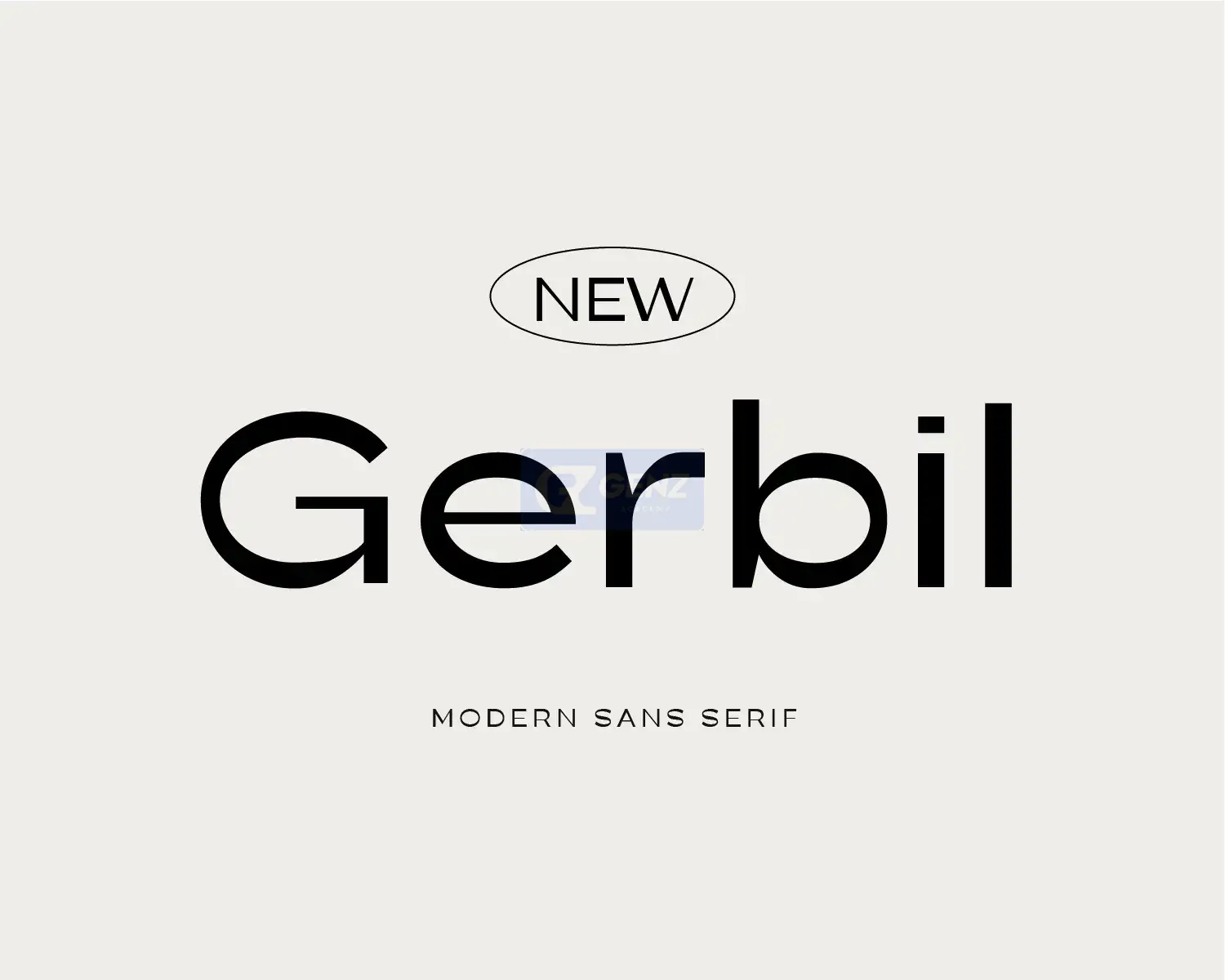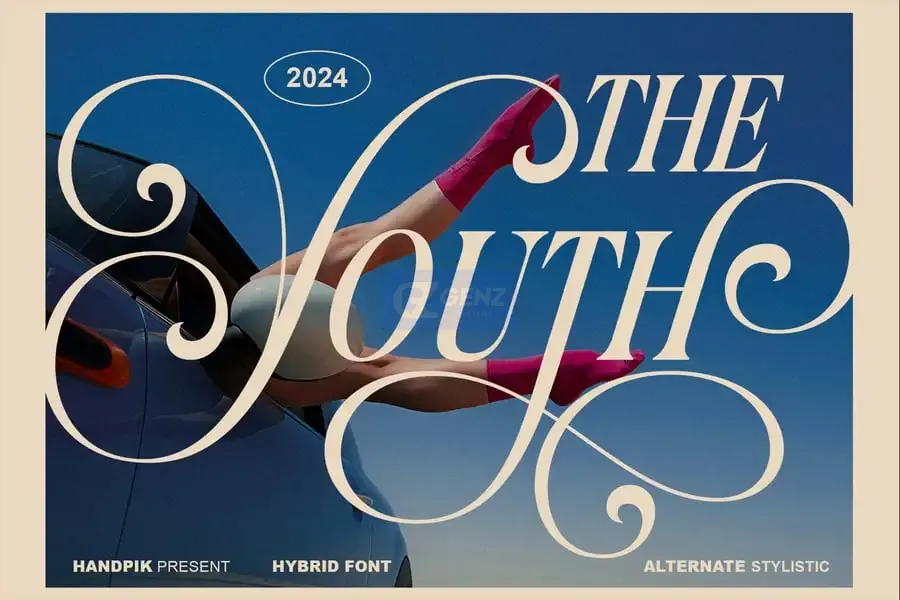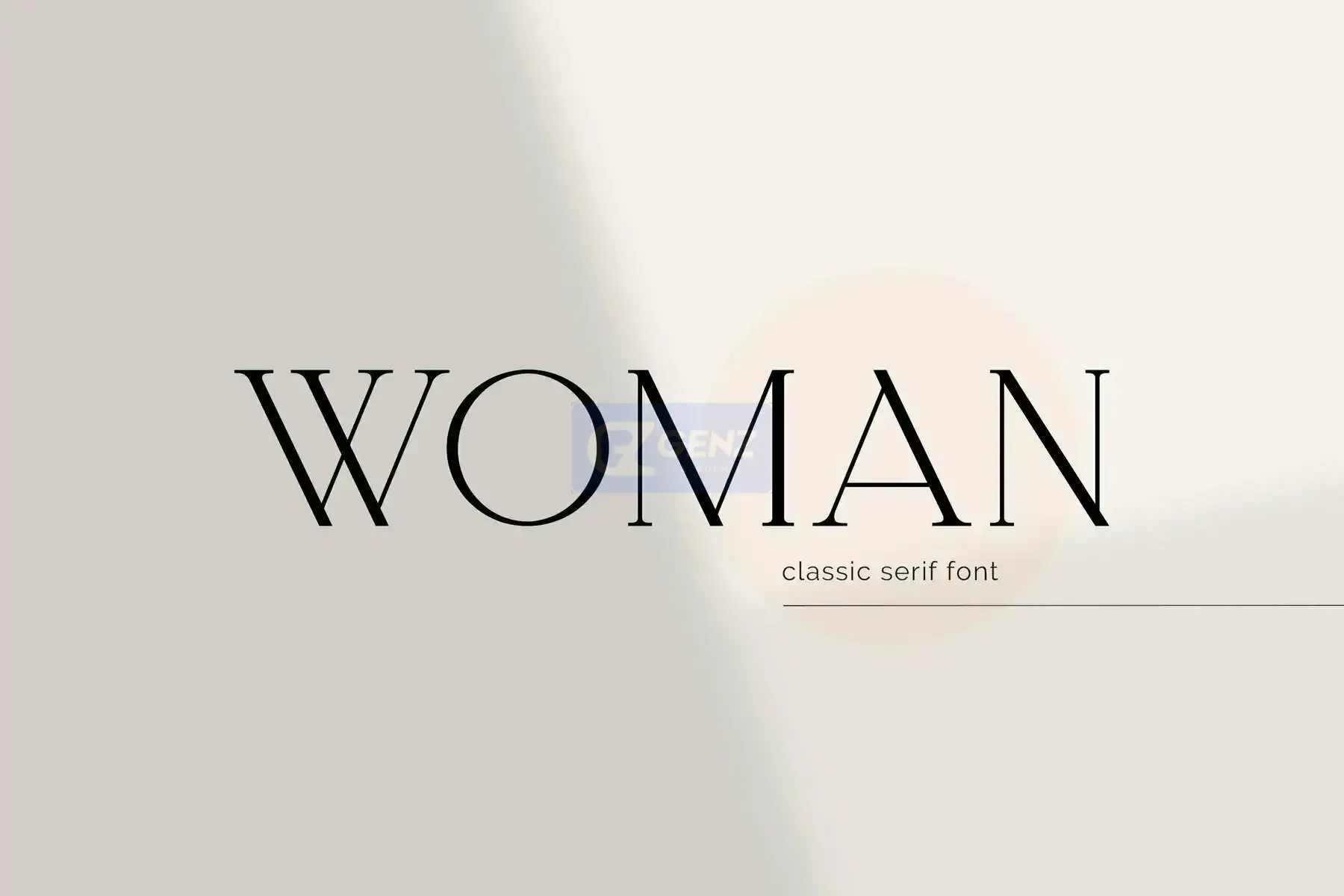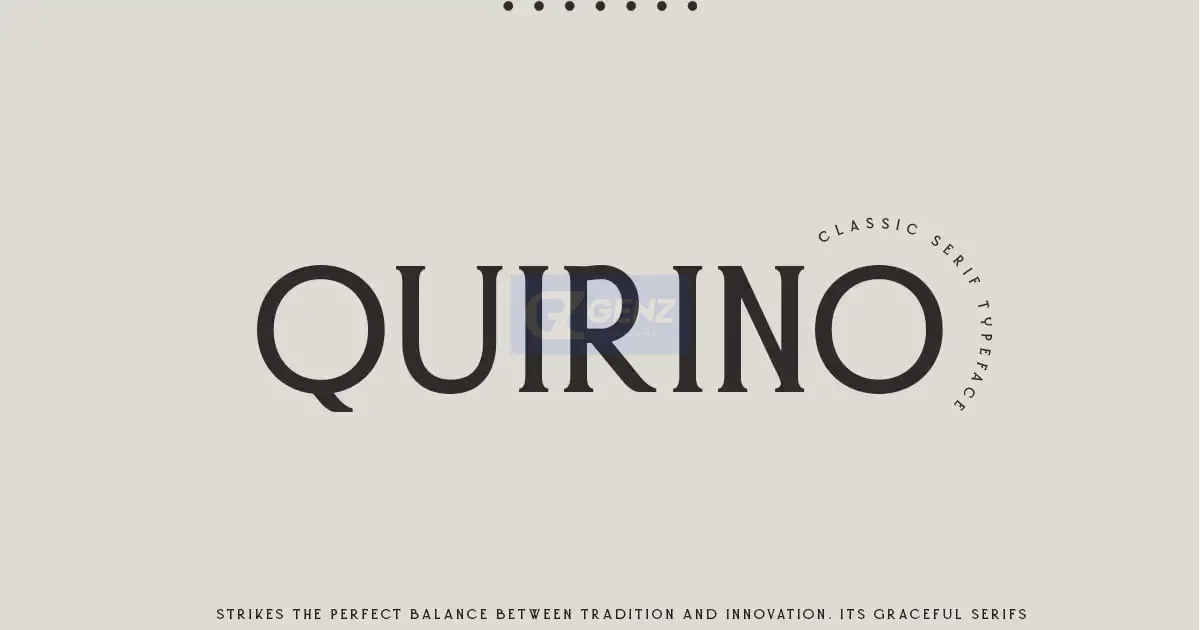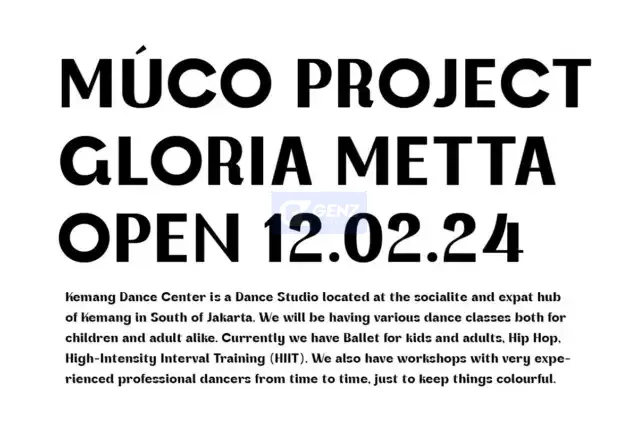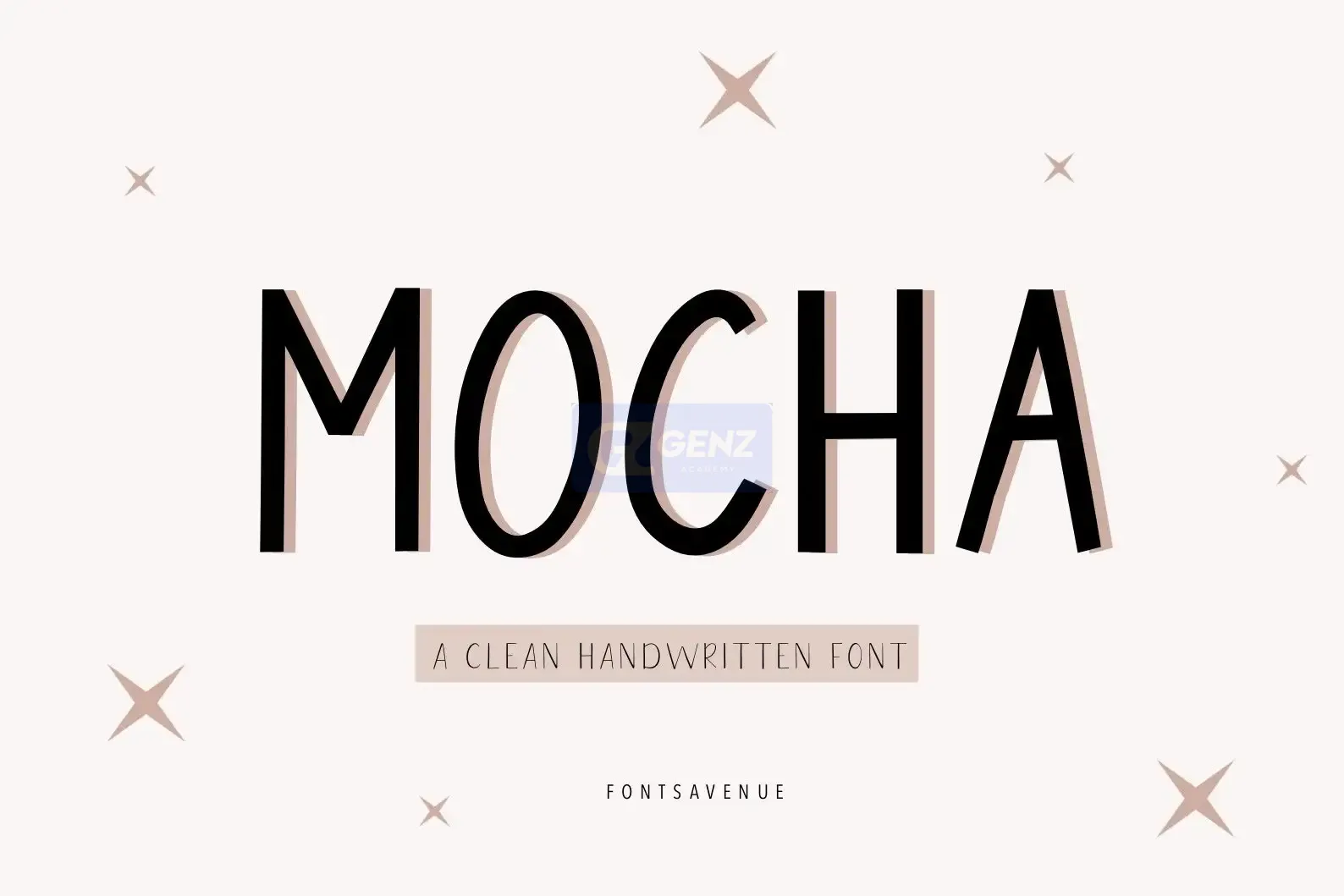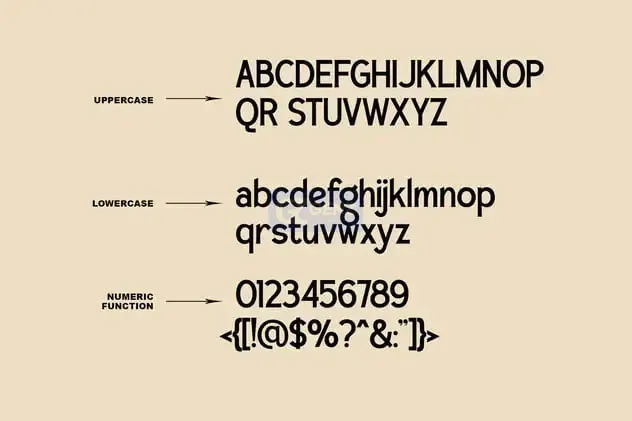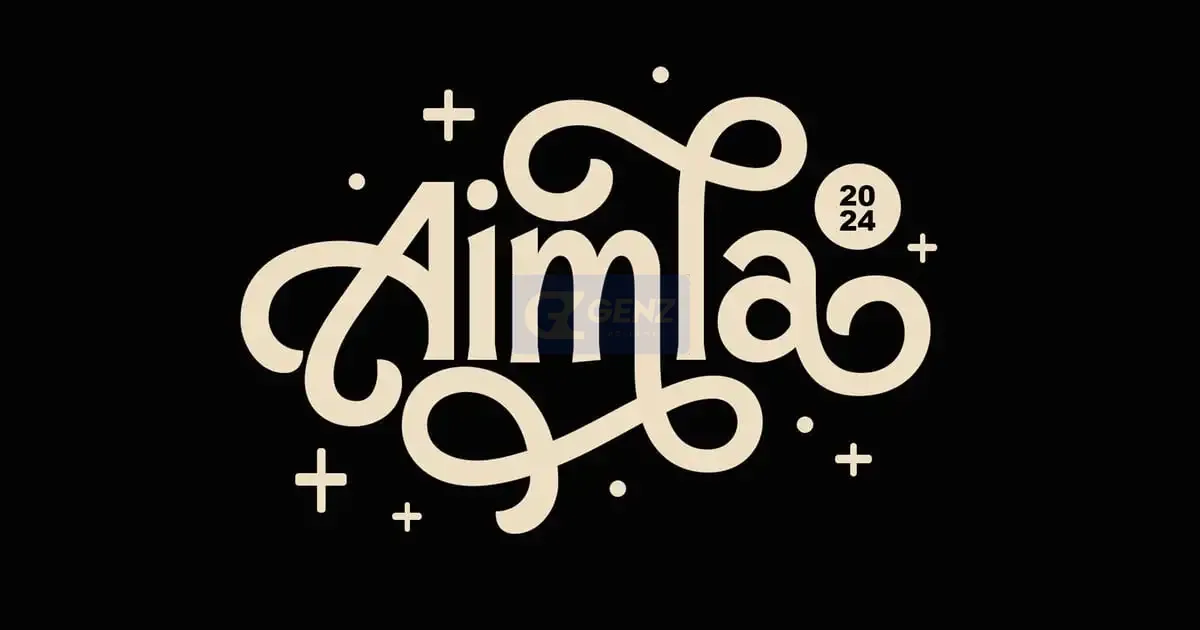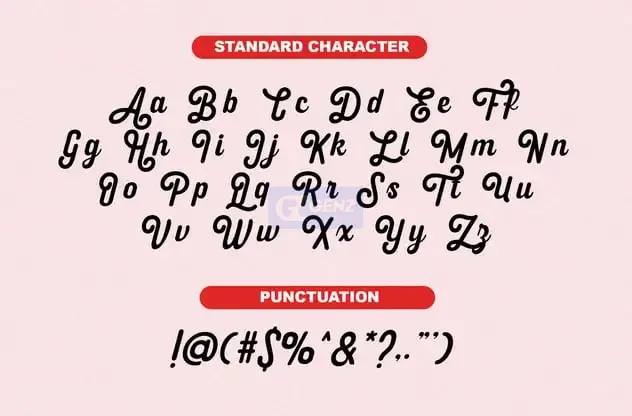
Trong thời đại công nghệ số hiện nay, việc lựa chọn font chữ phù hợp không chỉ tạo nên vẻ đẹp thẩm mỹ cho thiết kế mà còn giúp truyền tải thông điệp một cách mạnh mẽ và ấn tượng hơn. Năm 2025, các nhà thiết kế đồ họa và người dùng cần cập nhật những font chữ mới nhất để đáp ứng nhu cầu sáng tạo. Những font chữ không chỉ đẹp mắt mà còn đa dạng, có thể áp dụng cho nhiều dạng dự án khác nhau từ in ấn đến thiết kế số. Trong bài viết này, chúng ta sẽ cùng khám phá danh sách các font chữ tiếng Anh được yêu thích nhất và những trang web miễn phí để tải chúng về dễ dàng, tạo điều kiện cho bạn nâng cao chất lượng các sản phẩm thiết kế của mình.
Google Fonts: nguồn tài nguyên đáng tin cậy
Nói về Google Fonts, đây được coi là “báu vật” cho các nhà thiết kế không chỉ bởi vì số lượng font phong phú mà còn vì những tiện ích mà nó mang lại. Với hơn 1,800 font chữ mã nguồn mở, Google Fonts là một nơi tuyệt vời cho những ai đang tìm kiếm nguồn tài nguyên miễn phí để làm phong phú cho dự án thiết kế của mình.
Google Fonts không chỉ cung cấp font chữ mà còn hỗ trợ nhiều ngôn ngữ khác nhau, bao gồm cả tiếng Việt. Đây là một điểm cộng lớn, giúp bạn tùy chỉnh thiết kế theo đúng ý muốn mà không gặp phải vấn đề về ngôn ngữ. Ngoài ra, giao diện thân thiện và khả năng tích hợp đơn giản giúp người dùng dễ dàng nhúng các font chữ vào website hoặc dự án của họ.
Một số font chữ nổi bật từ Google Fonts có thể kể đến như:
- Roboto: Font chữ sans-serif hiện đại, dễ đọc, thường được sử dụng cho thiết kế web.
- Lato: Được thiết kế để đem lại sự cân bằng giữa hiện đại và truyền thống.
- Open Sans: Một trong những font phổ biến nhất trên thế giới với độ dễ đọc cao.
Tất cả các font này đều được thiết kế để người dùng có thể tùy chỉnh theo kích thước, màu sắc và độ dày chữ, giúp việc sử dụng trở nên thân thiện và linh hoạt hơn bao giờ hết.
Bảng so sánh một số font chữ nổi bật từ Google Fonts:
| Tên Font | Loại Font | Nơi Sử Dụng |
|---|---|---|
| Roboto | Sans-serif | Thiết kế web, tài liệu |
| Lato | Sans-serif | Website, in ấn |
| Open Sans | Sans-serif | Thông điệp quảng cáo |
Dafont: kho tàng font chữ độc đáo
Khi nói đến việc tìm kiếm các font chữ độc đáo và thú vị, Dafont là cái tên không thể thiếu. Đây là nơi quy tụ của hàng chục ngàn font chữ miễn phí với các chủ đề đa dạng từ cổ điển đến hiện đại, từ dễ thương đến trang nghiêm.
Dafont cho phép người dùng xem trước font trong thời gian thực bằng cách nhập văn bản của riêng mình, giúp xác định font chữ nào phù hợp nhất cho dự án của bạn. Đặc biệt, các font trên này được phân loại thành nhiều nhóm khác nhau giúp bạn dễ dàng tìm kiếm, như script, display, sans-serif, serif, … Đây chính là một ưu điểm vượt trội mà Dafont mang lại, giúp tiết kiệm thời gian cho các nhà thiết kế.
Như một người yêu thích font chữ, bạn sẽ tìm thấy rất nhiều font chữ thú vị tại Dafont. Hãy lưu ý đọc kỹ giấy phép sử dụng để tránh các vấn đề về bản quyền khi ứng dụng chúng trong dự án của mình.
Danh sách một số loại font chữ nổi bật trên Dafont:
- Black Jack: Font chữ viết tay đầy cá tính, thường được dùng cho thiết kế trẻ trung.
- Pacifico: Đem đến hơi thở của tự do và sáng tạo, rất độc đáo và nổi bật.
FontSpace: nền tảng tìm kiếm font chữ hữu ích
Nếu bạn đang tìm kiếm một nền tảng thân thiện và dễ sử dụng để khám phá các font chữ, FontSpace là nơi lý tưởng cho bạn. Với kho tàng hơn 120,000 font, đây là nơi tập trung của nhiều nhà thiết kế nổi tiếng trên thế giới. Giao diện trực quan và dễ điều hướng giúp người dùng tìm kiếm font một cách nhanh chóng và dễ dàng.
Tại FontSpace, người dùng có thể lọc font theo nhiều điều kiện khác nhau như phong cách, nhà thiết kế hay độ phổ biến, từ đó tạo ra bộ sưu tập font chữ yêu thích. Mỗi font chữ đều đi kèm với thông tin rõ ràng về giấy phép sử dụng, đảm bảo cho bạn rằng không gặp rắc rối về pháp lý sau này.
Bên cạnh đó, FontSpace cũng khuyến khích người dùng chia sẻ font chữ của chính mình, tạo ra một cộng đồng sáng tạo tích cực, nơi mọi người có thể trao đổi ý tưởng và thiết kế.
Một số font nổi bật trên FontSpace:
- Amatic SC: Font với kiểu chữ viết tay, đơn giản nhưng rất dễ nhớ.
- Quicksand: Phong cách hiện đại, rất phù hợp cho các dự án liên quan đến công nghệ.